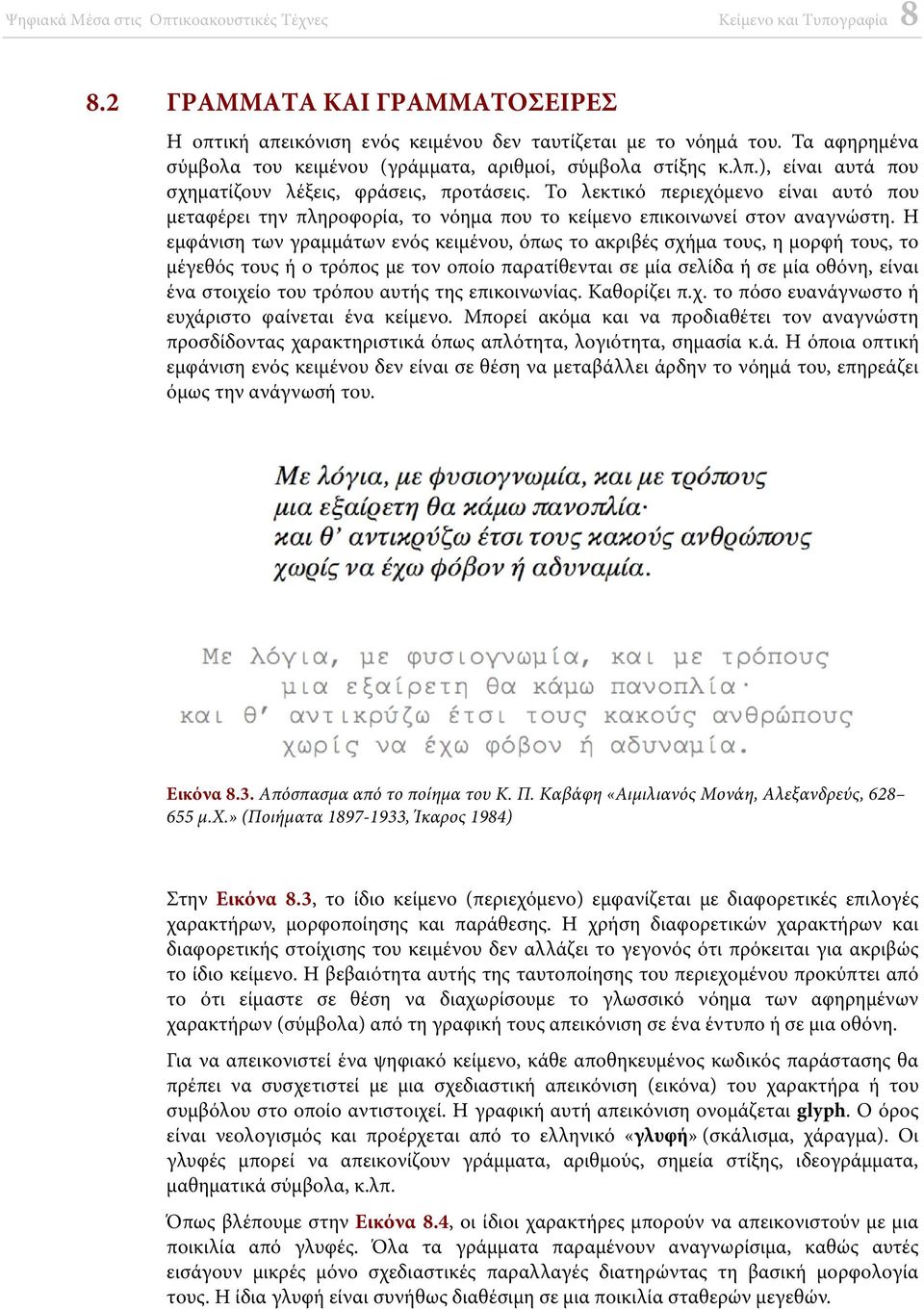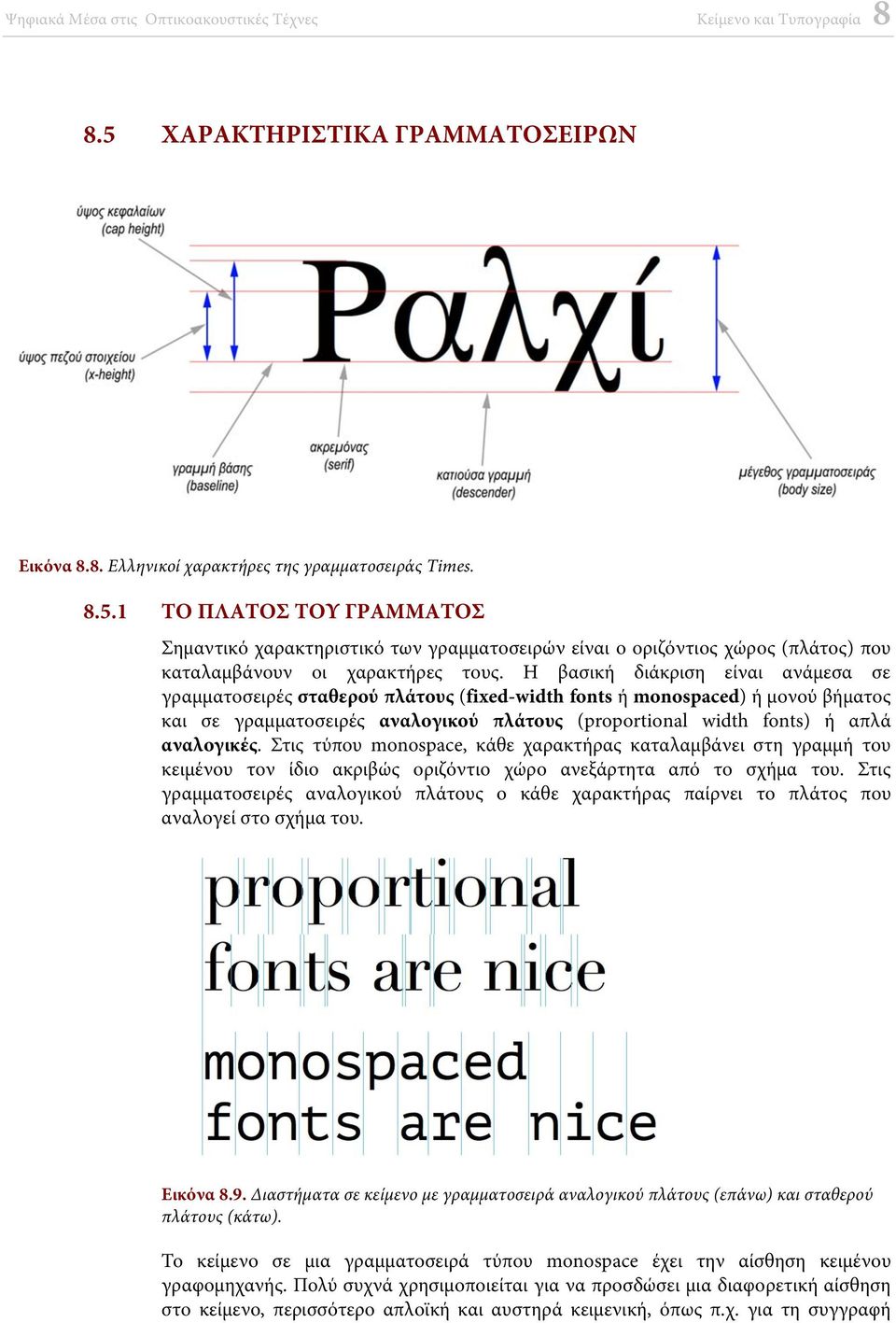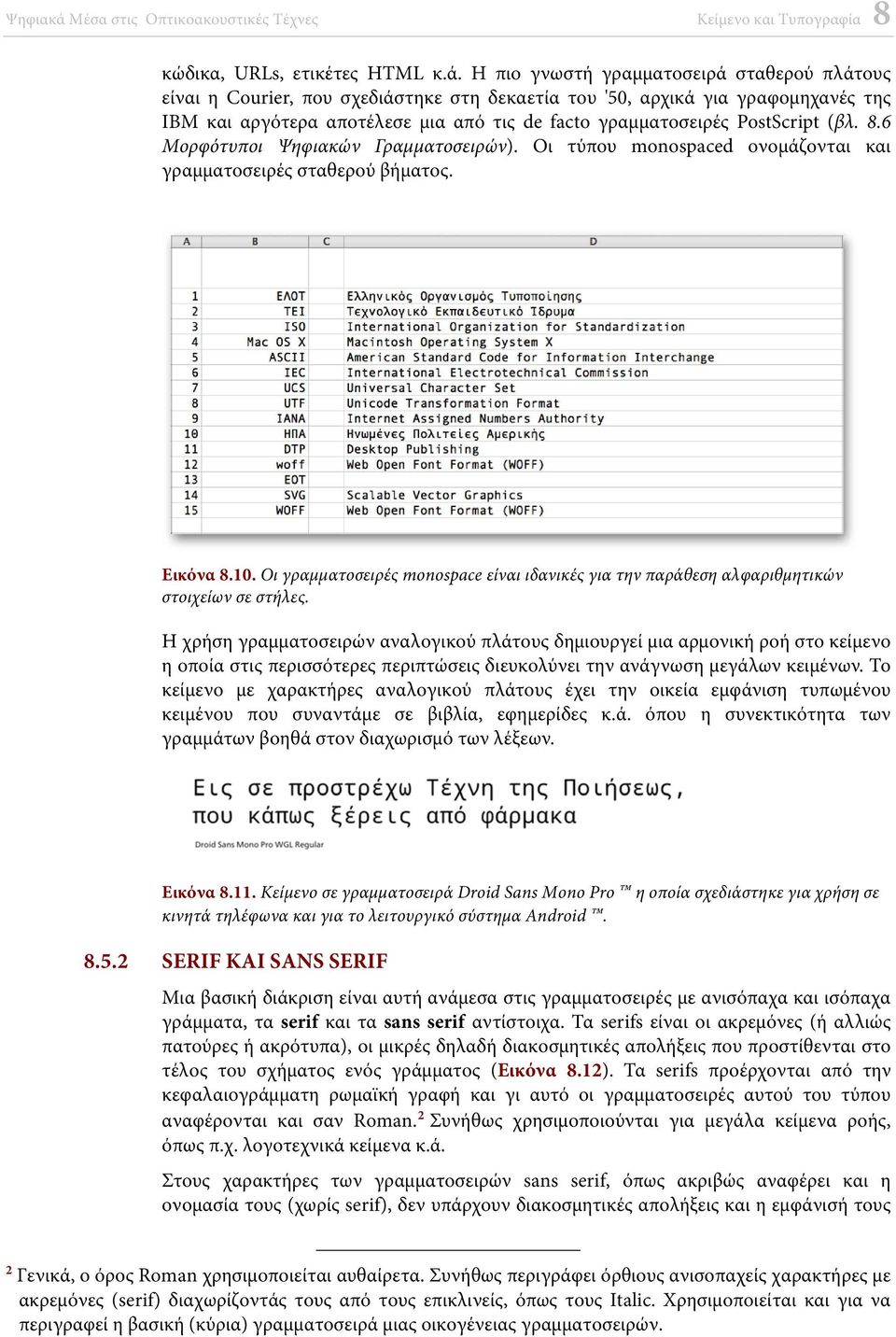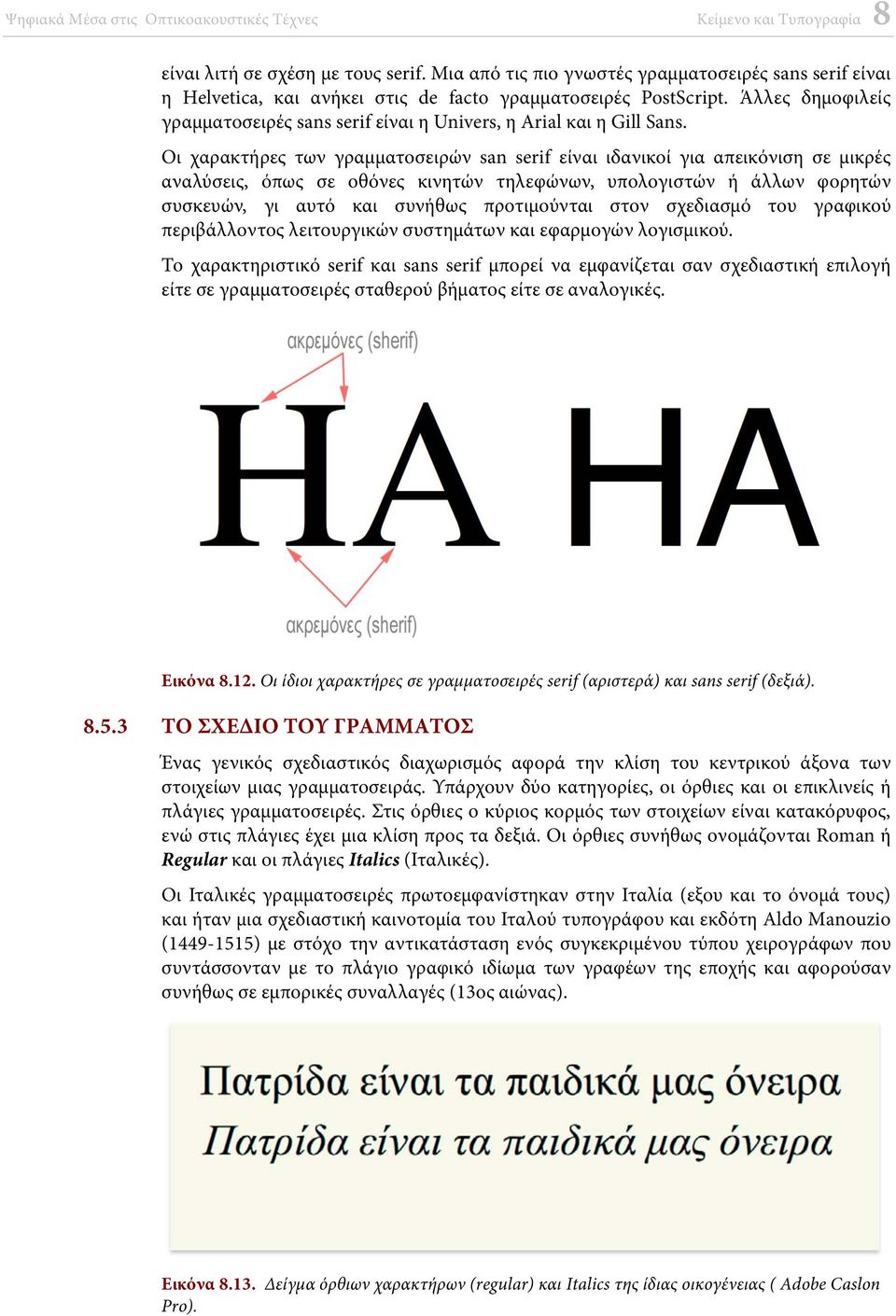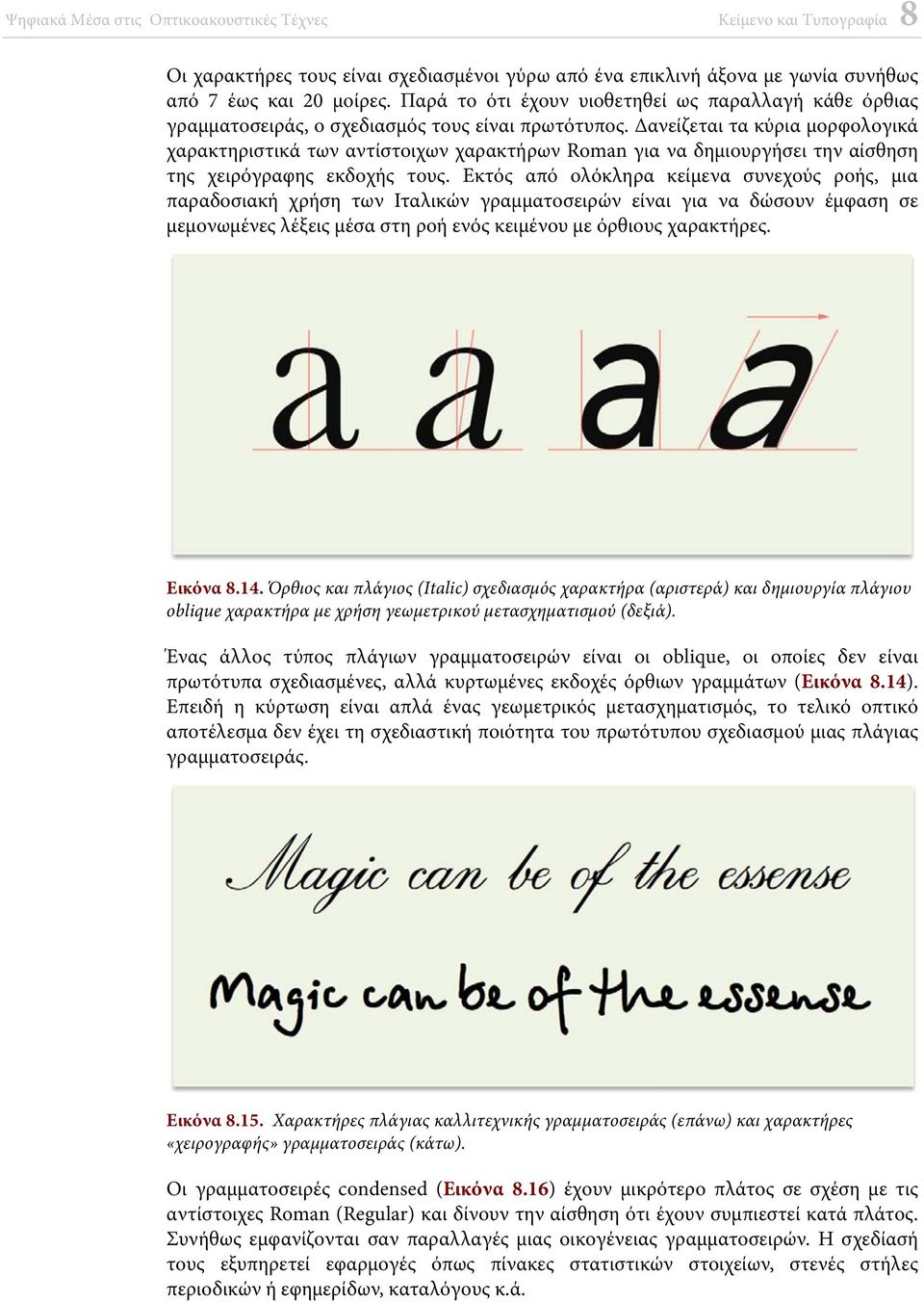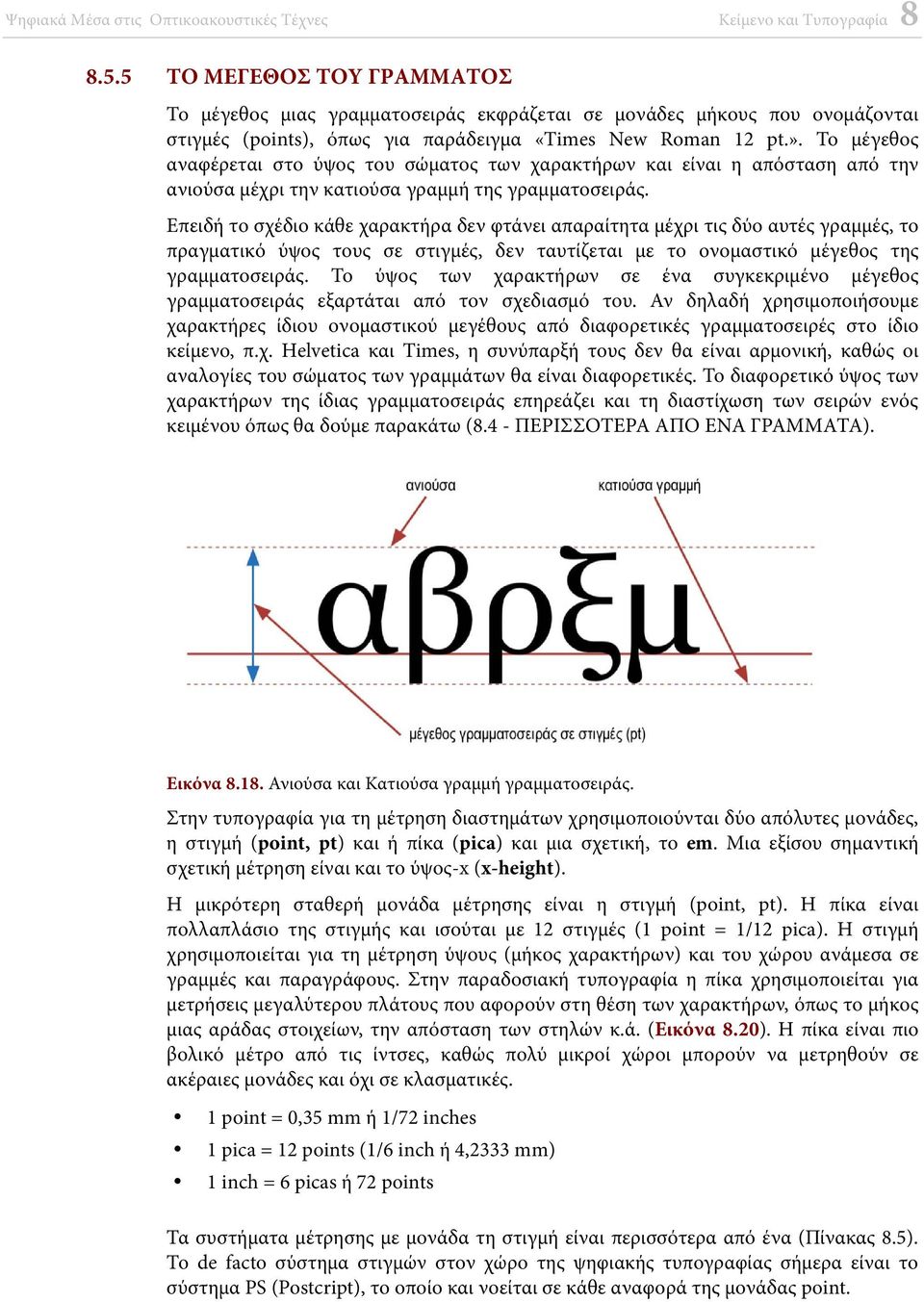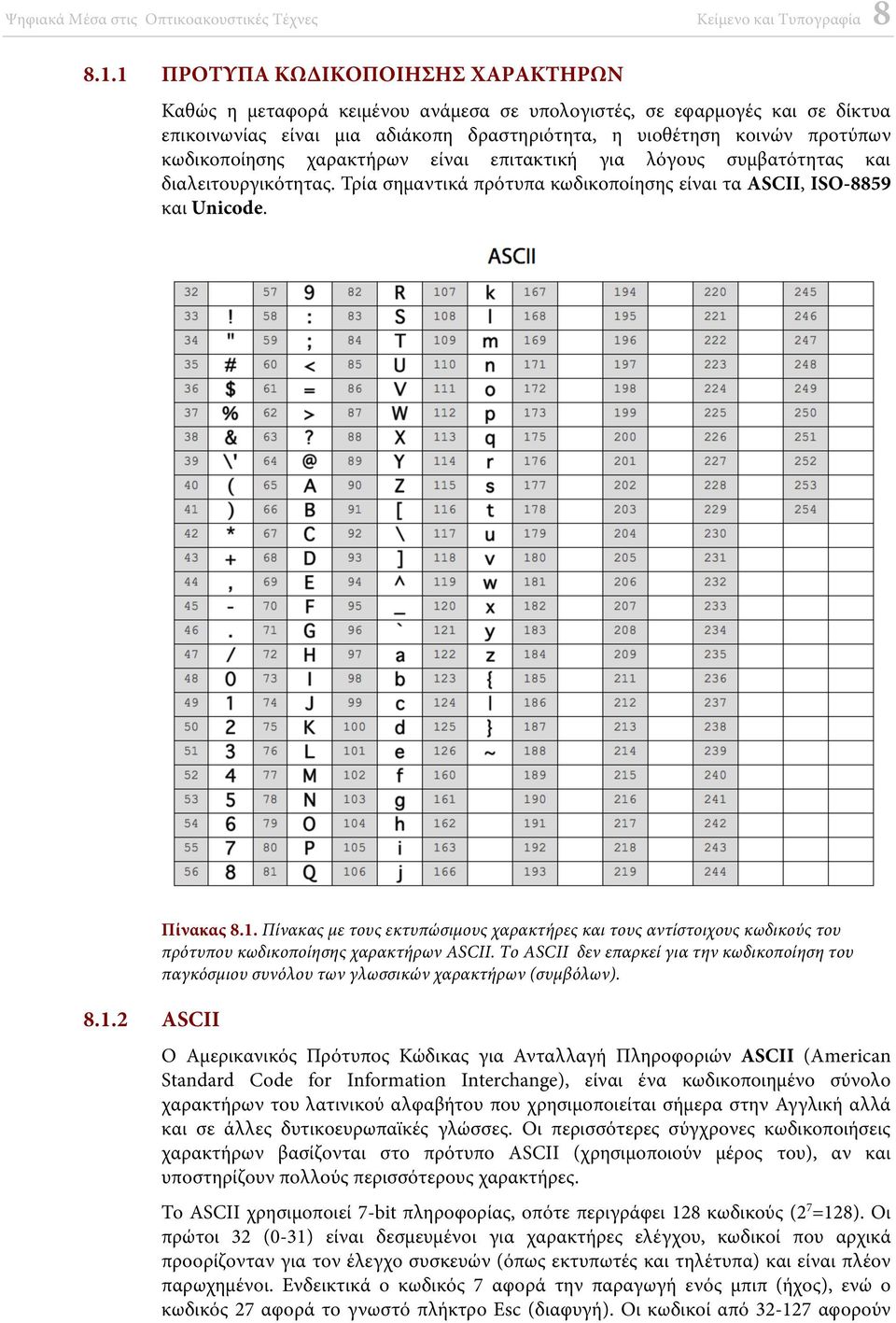
8 ΨΗΦΙΑΚΟ ΚΕΙΜΕΝΟ ΚΑΙ ΤΥΠΟΓΡΑΦΙΑ
3 Το κείμενο είναι η οπτική παράσταση της γλώσσας. Η γραφική αναπαράσταση των χαρακτήρων της γλώσσας (γράμματα, αριθμοί, σύμβολα κ.ά.), παίζει τον κεντρικό ρόλο, τόσο σε επίπεδο λειτουργικότητας του κειμένου, όσο και σε επίπεδο αισθητικής. Αν και η μορφολογική επιμέλεια κειμένων παραδοσιακά είναι ευθύνη του τυπογράφου ή του γραφίστα, η ευχέρεια που προσφέρουν οι υπολογιστές στη δημιουργία και στο σχεδιασμό κειμένου, όπως επίσης και η καθοριστική συμμετοχή του στα υπόλοιπα μέσα, επιβάλλει την εξοικείωση με τη σχετική τεχνολογία. Το ψηφιακό κείμενο έχει τις βάσεις του στις πρακτικές της κλασικής τυπογραφίας. 8.1 ΑΛΦΑΒΗΤΑ ΧΑΡΑΚΤΗΡΕΣ ΚΑΙ ΚΩΔΙΚΟΠΟΙΗΣΗ Η βάση της γραπτής μορφής κάθε γλώσσας είναι ένα συγκεκριμένο αλφάβητο, ένα δηλαδή σύνολο αφηρημένων συμβόλων (γράμματα, αριθμοί, μαθηματικά σύμβολα, ιδεογράμματα, σημεία στίξης, κ.ά.) τα οποία ονομάζονται χαρακτήρες. Παραδείγματα χαρακτήρων είναι το λατινικό «á», το ελληνικό «φ», το σύμβολο του copyright. Για να μπορέσουμε να παραστήσουμε τους χαρακτήρες ψηφιακά, θα πρέπει να καθορίσουμε μια αντιστοίχιση των αφηρημένων αυτών συμβόλων με δεδομένα που μπορούμε να αποθηκεύσουμε στον ηλεκτρονικό υπολογιστή. Αφού στον υπολογιστή μπορούμε να αποθηκεύσουμε μόνο δυαδικά δεδομένα (σειρές δυαδικών ψηφίων), οι συνδυασμοί των οποίων μπορούν να ερμηνευτούν ως ακέραιοι αριθμοί με βάση το 2, αρκεί να συσχετίσουμε τους χαρακτήρες με ακέραιους αριθμούς. Ένας τέτοιος συσχετισμός ονομάζεται κωδικοποιημένο σύνολο χαρακτήρων (coded character set) οι ακέραιοι αριθμοί ονομάζονται κωδικοί παράστασης (character set codes) ή κωδικά σημεία (code points) και το πεδίο ορισμού του (το αλφάβητο για το οποίο καθορίζεται ο συσχετισμός) ονομάζεται σύνολο χαρακτήρων (character set) ή αλλιώς ρεπερτόριο χαρακτήρων (character repertoire). Πολλές φορές χρησιμοποιείται και ο όρος charset ή κωδικοσελίδα (code page). Η κωδικοποίηση χαρακτήρων είναι το κλειδί για τη χαρτογράφηση των κωδικών σημείων (κατά συνέπεια και των χαρακτήρων που εκπροσωπούν) σε ψηφιακά δεδομένα στη μνήμη του υπολογιστή και για το αντίστροφο, την ανάγνωση δηλαδή των δεδομένων αυτών ως κωδικών σημείων. Τα κωδικοποιημένα σύνολα χαρακτήρων αφορούν αποκλειστικά στην κωδικοποίηση των χαρακτήρων ενός αλφαβήτου και όχι στην γραφική τους απεικόνιση στην οθόνη του υπολογιστή ή σε ένα έντυπο. Το πλήθος των χαρακτήρων που κωδικοποιούνται εξαρτάται από το σύστημα γραφής της κάθε γλώσσας. Τα φωνητικά συστήματα γραφής χρησιμοποιούν αλφάβητα, των οποίων τα σύμβολα ή οι διαφορετικοί συνδυασμοί τους, αντιπροσωπεύουν φθόγγους (ήχους). Τέτοια αλφάβητα είναι το ελληνικό, το λατινικό, το κυριλλικό. Το λατινικό αλφάβητο μπορεί να χρησιμοποιηθεί για περισσότερες από μία γλώσσες, όπως Γαλλικά, Γερμανικά και Αγγλικά. Χαρακτήρες που σχετίζονται με ένα φωνητικό σύστημα γραφής μπορούν τυπικά να κωδικοποιηθούν σε ένα byte (συλλαβή) των 8-bit, καθώς το ρεπερτόριο χαρακτήρων τους είναι συνήθως μικρότερο από 250. Τα ιδεογραφικά συστήματα γραφής χρησιμοποιούν ιδεογράμματα τα οποία αναπαριστούν το νόημα των λέξεων και όχι τους ήχους της γλώσσας. Τυπικά παραδείγματα είναι η γραφή της κινεζικής και ιαπωνικής γλώσσας. Τέτοιες γλώσσες συνήθως χρησιμοποιούν και συλλαβάρια, βοηθητικούς δηλαδή μηχανισμούς που επιτρέπουν την επικοινωνία της φωνητικής πληροφορίας. Χαρακτήρες που σχετίζονται με ένα ιδεογραφικό σύστημα γραφής απαιτούν κωδικοποίηση σε περισσότερα από ένα byte, καθώς το ρεπερτόριο τους μπορεί να περιλαμβάνει δεκάδες χιλιάδες σύμβολα.
4 8.1.1 ΠΡΟΤΥΠΑ ΚΩΔΙΚΟΠΟΙΗΣΗΣ ΧΑΡΑΚΤΗΡΩΝ Καθώς η μεταφορά κειμένου ανάμεσα σε υπολογιστές, σε εφαρμογές και σε δίκτυα επικοινωνίας είναι μια αδιάκοπη δραστηριότητα, η υιοθέτηση κοινών προτύπων κωδικοποίησης χαρακτήρων είναι επιτακτική για λόγους συμβατότητας και διαλειτουργικότητας. Τρία σημαντικά πρότυπα κωδικοποίησης είναι τα ASCII, ISO-8859 και Unicode ASCII Πίνακας 8.1. Πίνακας με τους εκτυπώσιμους χαρακτήρες και τους αντίστοιχους κωδικούς του πρότυπου κωδικοποίησης χαρακτήρων ASCII. Το ASCII δεν επαρκεί για την κωδικοποίηση του παγκόσμιου συνόλου των γλωσσικών χαρακτήρων (συμβόλων). Ο Αμερικανικός Πρότυπος Κώδικας για Ανταλλαγή Πληροφοριών ASCII (American Standard Code for Information Interchange), είναι ένα κωδικοποιημένο σύνολο χαρακτήρων του λατινικού αλφαβήτου που χρησιμοποιείται σήμερα στην Αγγλική αλλά και σε άλλες δυτικοευρωπαϊκές γλώσσες. Οι περισσότερες σύγχρονες κωδικοποιήσεις χαρακτήρων βασίζονται στο πρότυπο ASCII (χρησιμοποιούν μέρος του), αν και υποστηρίζουν πολλούς περισσότερους χαρακτήρες. Το ASCII χρησιμοποιεί 7-bit πληροφορίας, οπότε περιγράφει 128 κωδικούς (2 7 =128). Οι πρώτοι 32 (0-31) είναι δεσμευμένοι για χαρακτήρες ελέγχου, κωδικοί που αρχικά προορίζονταν για τον έλεγχο συσκευών (όπως εκτυπωτές και τηλέτυπα) και είναι πλέον παρωχημένοι. Ενδεικτικά ο κωδικός 7 αφορά την παραγωγή ενός μπιπ (ήχος), ενώ ο κωδικός 27 αφορά το γνωστό πλήκτρο Esc (διαφυγή). Οι κωδικοί από αφορούν
5 εκτυπώσιμους χαρακτήρες συμπεριλαμβανομένου του κενού διαστήματος ως αόρατου γραφικού. (κωδικός 32). Εικόνα 8.1. Η ίδια ιστοσελίδα με κείμενο κωδικοποιημένο σε UTF-8 (αριστερά) και η εμφάνισή της με την χρήση διαφορετικού charset (ISO ). Όταν το 1972 το ASCII τυποποιήθηκε σε διεθνές πρότυπο (ISO 646), δημιουργήθηκαν και κάποιες παραλλαγές του για να καλύψουν και άλλες γλώσσες (γράμματα με τόνους, σύμβολα νομισμάτων κ.λπ.). Η λύση αυτή δεν ήταν ικανοποιητική, καθώς η ανταλλαγή κωδικοποιημένων κειμένων απαιτούσε τη χρήση ακριβώς του ίδιου πρότυπου και από τις δύο πλευρές. Η λύση δόθηκε με την αύξηση των διαθέσιμων θέσεων κωδικών σε 256 χρησιμοποιώντας 8-bit πληροφορίας, αντί για 7-bit του ISO 646. Το σύνολο των 128 κωδικών του ASCII μπορούσε να μεταφερθεί απαράλλακτο στα νέα κωδικοποιημένα σύνολα χαρακτήρων. Η αλλαγή αυτή δημιούργησε μια πληθώρα παραλλαγών του ASCII σε 8-bit από διάφορους ενδιαφερόμενους κατασκευαστές, όλες από τις οποίες συμπεριελάμβαναν τους κωδικούς (ASCII). Οι υπόλοιπες διαθέσιμες 129 θέσεις κωδικών σημείων χρησιμοποιήθηκαν ανάλογα με το εκάστοτε ενδιαφέρον. Σε διαφορετικά δηλαδή πρότυπα, οι ίδιες θέσεις αντιστοιχούσαν σε διαφορετικά σύμβολα για τις δυτικοευρωπαϊκές χώρες, σε άλλα για το κυριλλικό αλφάβητο, άλλα για τους υπολογιστές Macintosh κ.λπ. Η επικοινωνία κειμένων, δηλαδή, είναι αποτελεσματική μόνο όταν και οι δύο πλευρές υιοθετήσουν την ίδια ακριβώς παραλλαγή κωδικοποίησης ISO 8859 Μια (αναποτελεσματική όπως αποδείχθηκε) λύση στο πρόβλημα της γλωσσικής συμβατότητας προσπάθησε να δώσει το πρότυπο ISO 8859 με παραλλαγές που απευθύνονταν σε διαφορετικές γλωσσικές ομάδες. Το βασικό πρότυπο είναι το ISO (αναφέρεται και ως ISO Latin1, ή απλά Latin1), το οποίο καλύπτει τις περισσότερες δυτικοευρωπαϊκές γλώσσες. Όπως και όλα τα κωδικοποιημένα σύνολα χαρακτήρων ISO 8859, το Latin1 είναι πρακτικά μια επέκταση του ASCII σε 8-bit η οποία διαθέτει συνολικά 256 διαθέσιμα κωδικά σημεία (βλ. Πίνακας 8.2). Παραλλαγές του ISO 8859 σχεδιάστηκαν για χώρες της ανατολικής Ευρώπης, όπως η Τσεχία, η Σλοβακία και η Κροατία (ISO ή Latin2), για γλώσσες που χρησιμοποιούν το κυριλλικό αλφάβητο (ISO ), το εβραϊκό (ISO ) κ.ά. Το πρότυπο για την ελληνική γλώσσα είναι το ISO (βλ. Πίνακας 8.3).
6 Η αποδοχή του ISO 8859 δεν είναι παγκόσμια, καθώς οι 256 θέσεις κωδικών σημείων δεν επαρκούν για την κωδικοποίηση όλων των χαρακτήρων κάθε γραφής. Επιπροσθέτως, δεν μπορεί να υποστηρίξει πολλαπλά αλφάβητα στον ίδιο υπολογιστή (μόνο το λατινικό και τους χαρακτήρες που έχει η συγκεκριμένη παραλλαγή). Παρόλα αυτά υπάρχουν πάρα πολλά κείμενα (π.χ. σε ιστοσελίδες κ.ά.) που έχουν κωδικοποιηθεί με παραλλαγές του ISO 8859, κάτι που (υπό συνθήκες) μπορεί να κάνει προβληματική την ανάγνωσή τους. Ανεπίσημες στατιστικές τοποθετούν τη χρήση του ISO Latin1 για την κωδικοποίηση κειμένου ιστοσελίδων στον παγκόσμιο ιστό σε ποσοστό περίπου 8% (Surveys 2015). Πίνακας 8.2. Το επάνω μέρος του πρότυπου ISO LATIN 1 (ISO ). Το κενό στον κωδικό 160 αντιστοιχεί στo διάστημα (space) που δεν ενεργοποιεί αλλαγή παραγράφου (non breaking space).
7 Πίνακας 8.3. Πίνακας με τους εκτυπώσιμους χαρακτήρες και τους αντίστοιχους κωδικούς του ISO (Greek). Άλλα προσωνύμιo είναι το ELOT 928, από το πρότυπο ΕΛΟΤ UNICODE Το Unicode είναι το κυρίαρχο πρότυπο για την κωδικοποίηση, αναπαράσταση και επεξεργασία χαρακτήρων κάθε συστήματος γραφής προσφέροντας ένα ομοιόμορφο τρόπο για την αποθήκευση, αναζήτηση και ανταλλαγή κειμένου, ανεξάρτητα υπολογιστικής πλατφόρμας, και γλώσσας. Αναπτύχθηκε και συντηρείται από το Unicode Consortium ( μια ανοικτή μη κερδοσκοπική κοινοπραξία με έδρα την Καλιφόρνια των ΗΠΑ και έχει υιοθετηθεί στο πρότυπο κωδικοποίησης ISO/IEC Η αρχιτεκτονική του Unicode είναι της τάξης των 16-bit και δίνει τη δυνατότητα της ανάθεσης μιας αποκλειστικής αριθμητικής τιμής και ονόματος σε καθένα χαρακτήρα ξεχωριστά οποιουδήποτε συστήματος γραφής στον κόσμο. Τα πρώτα διαθέσιμα κωδικά σημεία, τα οποία είναι δεσμευμένα για τους πιο κοινά χρησιμοποιούμενους χαρακτήρες, χωροθετούν μια περιοχή που ονομάζεται Βασικό Πολυγλωσσικό Επίπεδο ή αλλιώς BMP (Βasic Μultilingual Plane). To Unicode περιγράφει δεκαέξι ακόμα τέτοια συμπληρωματικά επίπεδα για την κωδικοποίηση άλλων χαρακτήρων και συμβόλων, προσφέροντας περίπου ένα εκατομμύριο θέσεις κωδικών σημείων, αρκετών για όλες τις γραφές του κόσμου όπως και για αρχαίες ιστορικές γραφές, κοινά συστήματα σημειογραφίας (π.χ. μουσικές νότες) κ.ά. (Unicode 2015)
8 8.1.5 Μορφές Κωδικοποίησης Unicode Η κωδικοποίηση χαρακτήρων δεν καθορίζει μόνο την ταυτότητα του κάθε χαρακτήρα και την αριθμητική του τιμή (κωδικό σημείο), αλλά και τον τρόπο με τον οποίο η τιμή αυτή αναπαριστάται στη μνήμη του υπολογιστή με τη μορφή δυαδικών ψηφίων (bits). Το Unicode υποστηρίζει τρεις μεθόδους κωδικοποίησης: UTF-8: (Universal Coded Character Set Transformation Format 8-bit). Χρησιμοποιεί ένα byte (8-bit) για την αναπαράσταση κάθε χαρακτήρα του συνόλου ASCII, δύο bytes (16-bit) για χαρακτήρες κάποιων άλλων επιπέδων και τρία bytes για τα υπόλοιπα επίπεδα του BMP. Για συμπληρωματικούς χαρακτήρες χρησιμοποιεί 4 bytes (32-bit). UTF-16: Χρησιμοποιεί 2 bytes (16-bit) για την κωδικοποίηση κάθε χαρακτήρα στο επίπεδο BMP και 4 bytes (32-bit) για συμπληρωματικούς χαρακτήρες. UTF-32: Χρησιμοποιεί 4 bytes (32-bit) για κάθε χαρακτήρα. Η πιο δημοφιλής από τις τρεις, η κωδικοποίηση κειμένου UTF-8 αποτελεί την defacto επιλογή για γλώσσες σήμανσης, όπως η HTML, αλλά και γλώσσες προγραμματισμού, όπως η Java. Το UTF-8 έχει επίσης υιοθετηθεί σαν πρότυπο και από τα κυρίαρχα λειτουργικά συστήματα Mac OS X και Windows. Όταν συστήματα γραφής για περισσότερες από μία γλώσσες μοιράζονται παρόμοια σύμβολα, η ένωση όλων αυτών των γραφικών αναπαραστάσεων αντιμετωπίζεται από το Unicode με ειδικούς αλγόριθμους μετασχηματισμών ως ένα μοναδικό ρεπερτόριο χαρακτήρων προς κωδικοποίηση και αναγνωρίζεται ως μια μοναδική γραφή. Κάθε τέτοιο ρεπερτόριο χαρακτήρων λειτουργεί ως βιβλιοθήκη και χρησιμοποιείται για τα συστήματα γραφής συγκεκριμένων γλωσσών. Σύμβολα της λατινικής γραφής για παράδειγμα, μπορούν να χρησιμοποιηθούν για δεκάδες ή και εκατοντάδες άλλες γλώσσες. Σε άλλες περιπτώσεις μόνο μια γλώσσα χρησιμοποιεί μια συγκεκριμένη γραφή, όπως η γραφή Hangeul για την Κορεατική, ή περισσότερες από μια γραφές, όπως στην Ιαπωνική. Η έκδοση Unicode 8.0 (Ιούνιος 2015) υποστηρίζει ένα ρεπερτόριο που ξεπερνά τους χαρακτήρες καλύπτοντας 129 σύγχρονες και αρχαίες γραφές συμπεριλαμβανομένων και πολλαπλών ρεπερτορίων συμβόλων, όπως αρχαίων ελληνικών αριθμών, βυζαντινής μουσικής σημειογραφίας κ.ά. (Πλήρης κατάλογος «Unicode 8.0 Character Code Charts», Unicode Charts) ISO/IEC Ο οργανισμός ISO σε συνεργασία με τον οργανισμό IEC (International Electrotechnical Commission) σχεδίασε το Παγκόσμιο Σύνολο Χαρακτήρων UCS (Universal Character Set), με κωδικοποίηση 32-bit, που πήρε την ονομασία ISO Το πρότυπο ISO και το Unicode διαθέτουν ακριβώς το ίδιο ρεπερτόριο χαρακτήρων με τους ίδιους κωδικούς. Η βασική διαφορά είναι ότι το Unicode προσθέτει προδιαγραφές που δεν εμπίπτουν στους σκοπούς του ISO 10646, το οποίο είναι ένα απλό σύστημα κωδικοποίησης χαρακτήρων, όπως και το ΙSO Αντιθέτως, το Unicode υποστηρίζει κανόνες για την αντιπαραβολή χαρακτήρων αλλά και τον αλγόριθμο για την αμφίδρομη ροή κειμένου που απαιτείται για γραφές όπως η Αραβική και η Εβραϊκή.
9 Η επιλογή της κωδικοποίησης ενός κειμένου με κάποιο επιθυμητό πρότυπο γίνεται εύκολα μέσω των εφαρμογών που το επιτρέπουν (Εικόνα 8.2). Μια από τις πρώτες ρυθμίσεις προτιμήσεων μιας εφαρμογής που χρησιμοποιεί κείμενο (επεξεργασίας κειμένου, σελιδοποίησης, δημιουργίας ιστοσελίδων, κ.ά.) είναι η επιλογή κωδικοποίησης. Στην περίπτωση που δεν είναι διαθέσιμη, κατά πάσα πιθανότητα το όποιο κείμενο κωδικοποιείται με την εγγενή κωδικοποίηση του συστήματος. Σε κάθε περίπτωση είναι καλή πρακτική να γνωρίζουμε την κωδικοποίηση του κειμένου. Εικόνα 8.2. Επιλογές κωδικοποίησης κειμένου της εφαρμογής επεξεργασίας κειμένου Text Edit της Apple (MacOSX)
10 8.2 ΓΡΑΜΜΑΤΑ ΚΑΙ ΓΡΑΜΜΑΤΟΣΕΙΡΕΣ Η οπτική απεικόνιση ενός κειμένου δεν ταυτίζεται με το νόημά του. Τα αφηρημένα σύμβολα του κειμένου (γράμματα, αριθμοί, σύμβολα στίξης κ.λπ.), είναι αυτά που σχηματίζουν λέξεις, φράσεις, προτάσεις. Το λεκτικό περιεχόμενο είναι αυτό που μεταφέρει την πληροφορία, το νόημα που το κείμενο επικοινωνεί στον αναγνώστη. Η εμφάνιση των γραμμάτων ενός κειμένου, όπως το ακριβές σχήμα τους, η μορφή τους, το μέγεθός τους ή ο τρόπος με τον οποίο παρατίθενται σε μία σελίδα ή σε μία οθόνη, είναι ένα στοιχείο του τρόπου αυτής της επικοινωνίας. Καθορίζει π.χ. το πόσο ευανάγνωστο ή ευχάριστο φαίνεται ένα κείμενο. Μπορεί ακόμα και να προδιαθέτει τον αναγνώστη προσδίδοντας χαρακτηριστικά όπως απλότητα, λογιότητα, σημασία κ.ά. Η όποια οπτική εμφάνιση ενός κειμένου δεν είναι σε θέση να μεταβάλλει άρδην το νόημά του, επηρεάζει όμως την ανάγνωσή του. Εικόνα 8.3. Απόσπασμα από το ποίημα του Κ. Π. Καβάφη «Αιμιλιανός Μονάη, Αλεξανδρεύς, μ.x.» (Ποιήματα , Ίκαρος 1984) Στην Εικόνα 8.3, το ίδιο κείμενο (περιεχόμενο) εμφανίζεται με διαφορετικές επιλογές χαρακτήρων, μορφοποίησης και παράθεσης. Η χρήση διαφορετικών χαρακτήρων και διαφορετικής στοίχισης του κειμένου δεν αλλάζει το γεγονός ότι πρόκειται για ακριβώς το ίδιο κείμενο. Η βεβαιότητα αυτής της ταυτοποίησης του περιεχομένου προκύπτει από το ότι είμαστε σε θέση να διαχωρίσουμε το γλωσσικό νόημα των αφηρημένων χαρακτήρων (σύμβολα) από τη γραφική τους απεικόνιση σε ένα έντυπο ή σε μια οθόνη. Για να απεικονιστεί ένα ψηφιακό κείμενο, κάθε αποθηκευμένος κωδικός παράστασης θα πρέπει να συσχετιστεί με μια σχεδιαστική απεικόνιση (εικόνα) του χαρακτήρα ή του συμβόλου στο οποίο αντιστοιχεί. Η γραφική αυτή απεικόνιση ονομάζεται glyph. Ο όρος είναι νεολογισμός και προέρχεται από το ελληνικό «γλυφή» (σκάλισμα, χάραγμα). Οι γλυφές μπορεί να απεικονίζουν γράμματα, αριθμούς, σημεία στίξης, ιδεογράμματα, μαθηματικά σύμβολα, κ.λπ. Όπως βλέπουμε στην Εικόνα 8.4, οι ίδιοι χαρακτήρες μπορούν να απεικονιστούν με μια ποικιλία από γλυφές. Όλα τα γράμματα παραμένουν αναγνωρίσιμα, καθώς αυτές εισάγουν μικρές μόνο σχεδιαστικές παραλλαγές διατηρώντας τη βασική μορφολογία τους. Η ίδια γλυφή είναι συνήθως διαθέσιμη σε μια ποικιλία σταθερών μεγεθών.
11 Εικόνα 8.4. Η απεικόνιση των ίδιων χαρακτήρων με διαφορετικές γλυφές. Οι γλυφές οργανώνονται σε συλλογές οι οποίες ονομάζονται γραμματοσειρές (fonts). Οι γραμματοσειρές με τα ίδια βασικά σχεδιαστικά χαρακτηριστικά οργανώνονται σε οικογένειες (βλ. Ενότητα Οικογένειες). Ο όρος font(s) 1 είναι δανικός από τον χώρο της παραδοσιακής τυπογραφίας, όπου τα κινητά τυπογραφικά στοιχεία χυτεύονταν από λιωμένο μέταλλο σε εκμαγεία. Η χειρωνακτική συναρμολόγηση των μεταλλικών τυπογραφικών στοιχείων σε σειρές μέσα σε ένα μεταλλικό πλαίσιο δημιουργούσε ένα ανάστροφο ανάγλυφο του κειμένου. Η εκτύπωση γινόταν με τη μελάνωση της επιφάνειας του ανάγλυφου και την πίεση του χαρτιού πάνω σε αυτή (αναγλυφοτυπία). Η στοιχειοθεσία στο χέρι ξεπεράστηκε από μηχανικές τεχνολογίες χύτευσης και στοιχειοθεσίας όπως η Μονοτυπία και η Λινοτυπία, οι οποίες με τη σειρά τους έχουν πλέον αντικατασταθεί από την ψηφιακή τεχνολογία. Ιστορικά, ο όρος font αντιστοιχούσε στα κινητά μεταλλικά τυπογραφικά στοιχεία συγκεκριμένου μεγέθους μιας συγκεκριμένης γραμματοσειράς (π.χ. Times Bold Italics 12 pt). Κάθε παραλλαγή τους σε μέγεθος ή άλλη σχεδιαστική εκδοχή (έντονα, πλάγια κ.λπ.) ήταν ένα άλλο font. Στην εποχή της ψηφιακής στοιχειοθεσίας ο όρος font αναφέρεται σε μια συγκεκριμένη γραμματοσειρά, η οποία μπορεί να απεικονιστεί και να εκτυπωθεί σε οποιοδήποτε μέγεθος. Τη θέση των συλλογών μοναδικών τυπογραφικών στοιχείων έχουν πάρει πλέον τα ψηφιακά δεδομένα (ψηφιακά αρχεία γραμματοσειρών), τα οποία περιγράφουν την γραφική απεικόνιση των χαρακτήρων. Οι γραμματοσειρές περιγράφουν αλφαβητικούς και αριθμητικούς χαρακτήρες, σημεία στίξης, σύμβολα κ.ά. Μπορεί, επίσης, να περιγράφουν αποκλειστικά ιδεογράμματα και σύμβολα, όπως μαθηματικά σύμβολα, μουσικές νότες, σύμβολα χαρτογράφησης κ.ά. 1 Προέρχεται από τη λέξη fountry που σημαίνει χυτήριο.
12 8.3 Η ΠΡΟΣΒΑΣΗ ΣΕ ΓΡΑΜΜΑΤΟΣΕΙΡΕΣ Η πρόσβαση του υπολογιστή και των εφαρμογών του σε γραμματοσειρές γίνεται από: ψηφιακά αρχεία γραμματοσειρών που είναι ήδη εγκαταστημένα στο σύστημα του υπολογιστή (system fonts) γραμματοσειρές που έχουν ενσωματωθεί σε ένα αρχείο (embedded fonts) γραμματοσειρές που βρίσκονται σε ένα απομακρυσμένο εξυπηρετητή (web fonts) Εικόνα 8.5. Αποθηκευμένες γραμματοσειρές τύπου OpenType (OTF), σε σχετική βιβλιοθήκη του λειτουργικού συστήματος Mac OSX. Αν οι γραμματοσειρές έχουν ήδη ενσωματωθεί στο ψηφιακό αρχείο που εμπεριέχει το κείμενο, όπως π.χ. σε αρχεία PDF, αυτό σημαίνει ότι ήταν διαθέσιμες στον υπολογιστή που δημιούργησε το αρχείο και ότι ο χρήστης θα δει το κείμενο όπως αρχικά είχε σχεδιαστεί. Αν οι γραμματοσειρές δεν έχουν ενσωματωθεί στο αρχείο και δεν υπάρχει η δυνατότητα να βρεθούν σε κάποιο εξυπηρετητή μέσω διαδικτύου, αυτό σημαίνει ότι η εμφάνιση του κειμένου θα εξαρτάται από τις εγκατεστημένες γραμματοσειρές που διαθέτει ο χρήστης στον δικό του υπολογιστή (system fonts). Στην περίπτωση που δεν είναι διαθέσιμες, υπάρχει περίπτωση το κείμενο να μη διαβάζεται καθόλου ή να απεικονίζεται με άλλες γραμματοσειρές. Αν και η αντικατάστασή τους με τις όποιες διαθέσιμες είναι το πιο πιθανό σενάριο, το τελικό κείμενο δεν θα είναι αυτό που είχε αρχικά σχεδιαστεί. Ένας λόγος για τον οποίο οι γραμματοσειρές δεν ενσωματώνονται πάντοτε σε αρχεία κειμένου είναι γιατί δεν υπάρχει η δυνατότητα. Στα αρχεία HTML π.χ. δεν υπάρχει η δυνατότητα ενσωμάτωσης γραμματοσειρών, αλλά μόνο η δήλωση για το ποιες προτιμούνται για την αναπαράσταση του κειμένου (από τις ήδη εγκαταστημένες στον υπολογιστή του χρήστη ή από αποθηκευμένες σε εξυπηρετητές στο διαδίκτυο). Ένας άλλος λόγος θα μπορούσε να ήταν η αύξηση του μεγέθους του αρχείου λόγω της ενσωμάτωσης επιπρόσθετων δεδομένων σε αυτό.